タイププロジェクトのデザイナー達に「日本語で使用されている文字(漢字・ひらがな・カタカナ・ラテンアルファベット)以外の文字で興味がある、またはデザインしてみたい文字」は何かを聞いてみました。
複数回答があったのは韓国語で使用されている文字の「ハングル」です。 興味を持った理由は下記のようなものでした。
完全に見た目から入っていますが、幾何形態っぽいのと、字のパーツのルールに興味があります。
非母国語者の私から見ると形がかわいいので興味がある
幾何図形のようなパーツがパズルのように組み合わさって文字を構成しているところが面白い。
韓国語の勉強を始めて実際に文字を使うようになってさらに興味が深まった。
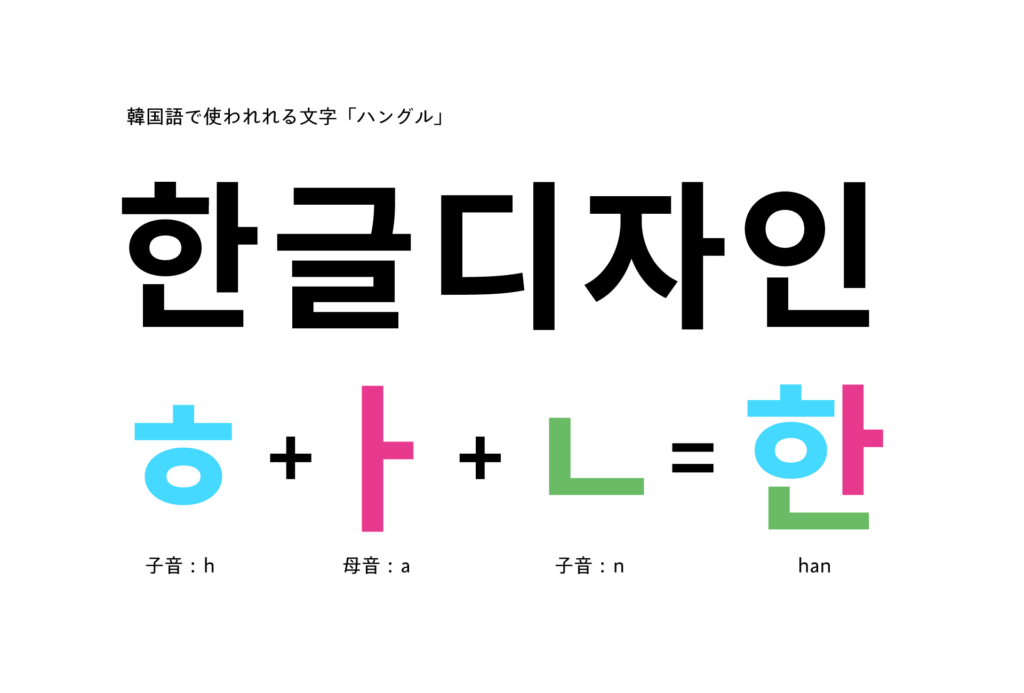
幾何図形のようなフォルムと、日本語の文字形態とは異なる点にタイププロジェクトのデザイナー達は興味を惹かれているようです。
日本語で使われる漢字が1文字1文字が「意味」を表す表意文字なのに対し、ハングルは仮名やラテンアルファベットのように「音」を表す表音文字です。 そして一つ一つの文字が独自の形を持つ仮名と違い、子音・母音を表すパーツが特定のルールに則って組み合わさることによって1文字を構成しています。
公共交通機関でも日本語・英語に加えて韓国語表記のサインが掲示されているところもありますし、最近では韓国ドラマやK-pop人気の影響で韓国の広告や商品を街中で見かける機会も増えたように感じます。
読者の皆さんの中にもハングルに興味を持っている方がいらっしゃるのではないでしょうか。